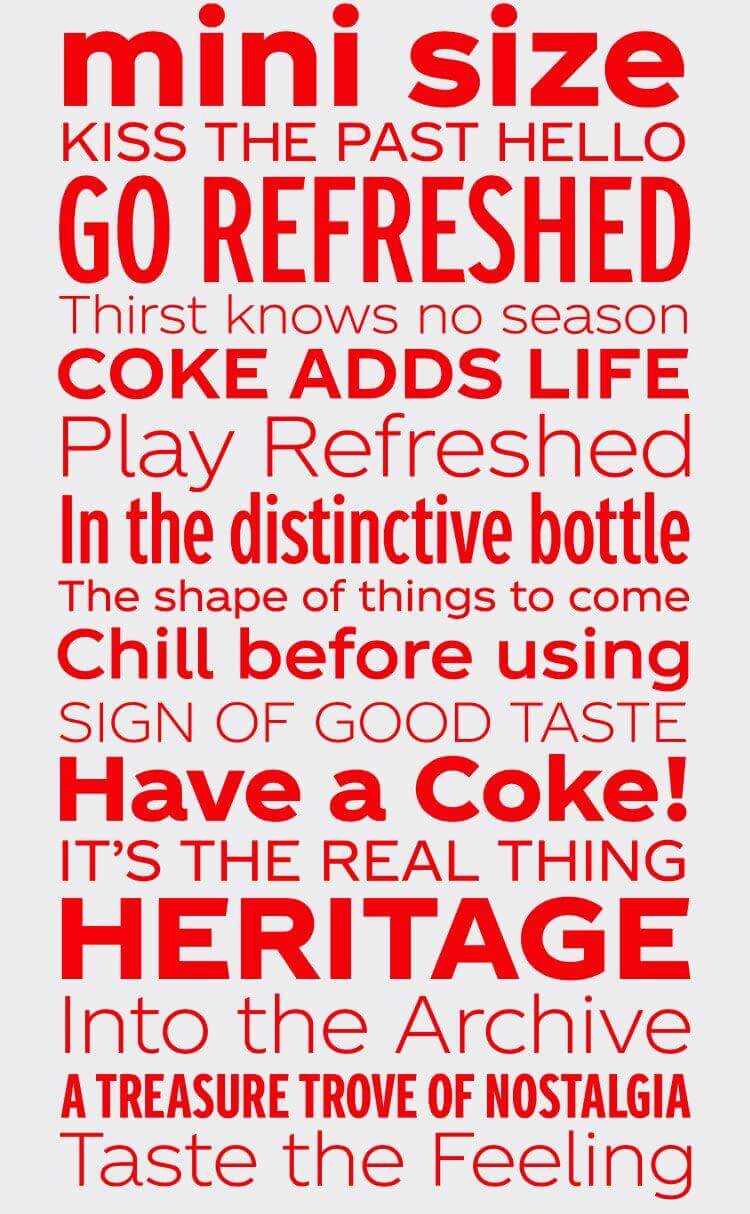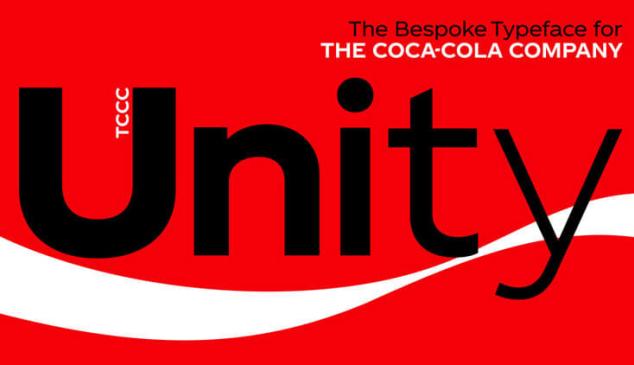
Coca-Cola ha lanzado, por primera vez en sus 130 años de historia, su propia tipografía inspirada en el diseño de la marca.
El nombre de la misma, TCCC Unity, viene del propio nombre de la compañía: The Coca-Cola Company. Ha sido diseñada por Brody Associates junto al equipo de diseñadores de Coca-Cola.
El diseño de la tipografía
La tipografía se inspira en el movimiento modernista americano de finales del siglo XIX e inicios del XX. Su aspecto circular y geométrico refleja la historia visual de la marca, como su logotipo, packaging y sus campañas de publicidad.
La tipografía ha sido creada para ser usada en múltiples plataformas, incluyendo digital y medios impresos.
También se ha creado la aplicación TCCC Unity para ofrecer más información sobre el diseño y desarrollo del proyecto. Incluye imágenes de los archivos gráficos de Coca-Cola, así como entrevistas con varios protagonistas que han trabajado en esta iniciativa como el Vicepresidente de la compañía, James Sommerville.